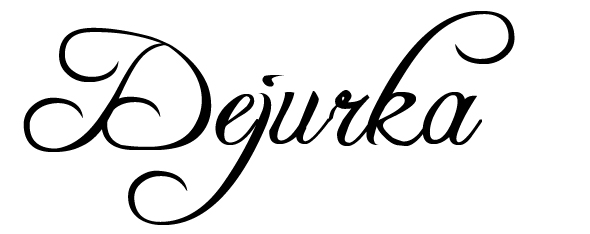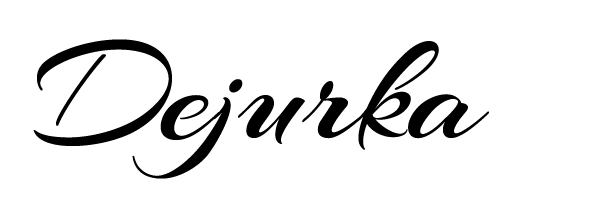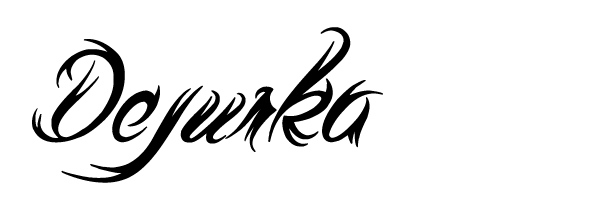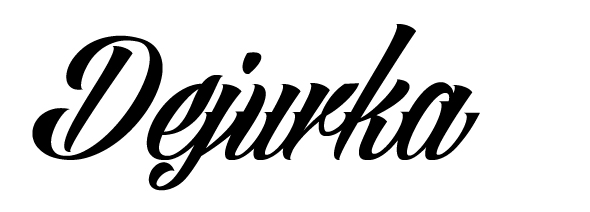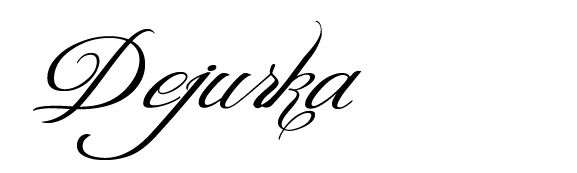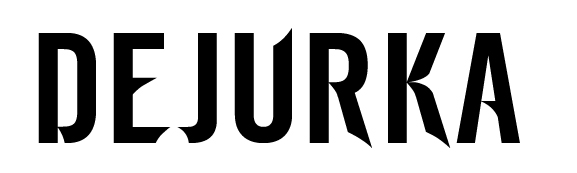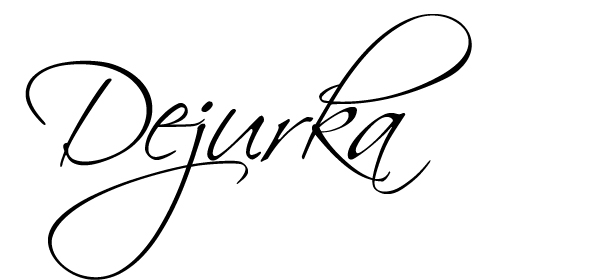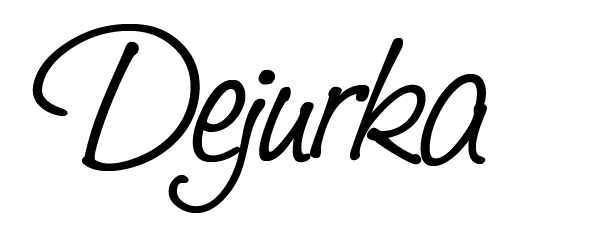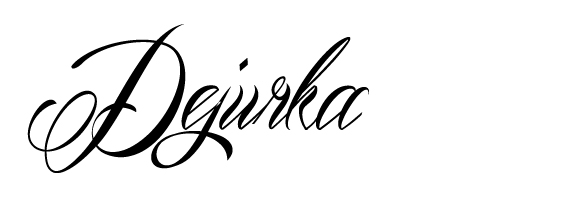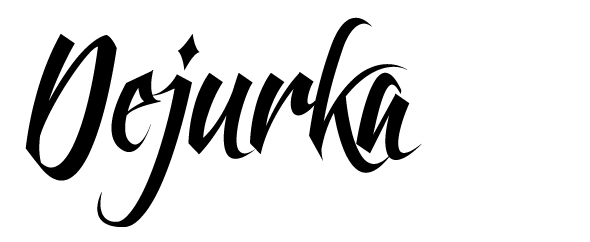
Подборка шрифтов для тату-надписей
Сегодня очень популярным стало набивание тату в виде надписей. Очень важным этапом является выбор правильного шрифта, ведь шрифтов существует тысячи, а когда дело подходит к выбору нужного, начинаются сюрпризы. Также нужно учитывать размер слов, месторасположения рисунка, помнить, что не все заглавные буквы шрифтов выглядят привлекательно. Мужские надписи чаще всего делаются с применением печатных букв, более жирного шрифта, с заостренными окончаниями, женщины выбирают шрифт с тонкими линиями, глубокими изгибами и дополнительными украшениями. Мы подобрали несколько вариантом подобных шрифтов.
Antlers
Lina Script
VTC Bad Tattoo Hand One
Saginaw
VTC Nue Tattoo Script
Mardian
Feathergraphy
Ford script
Great Vibes
Freebooter
Renaissance
ARIZONIA
Tribal Script
Angilla
Shit Happens
CM Tattoo Dragon
Tattoo
Scriptina
Champignon
Gabrielle
Heidorn Hill Font